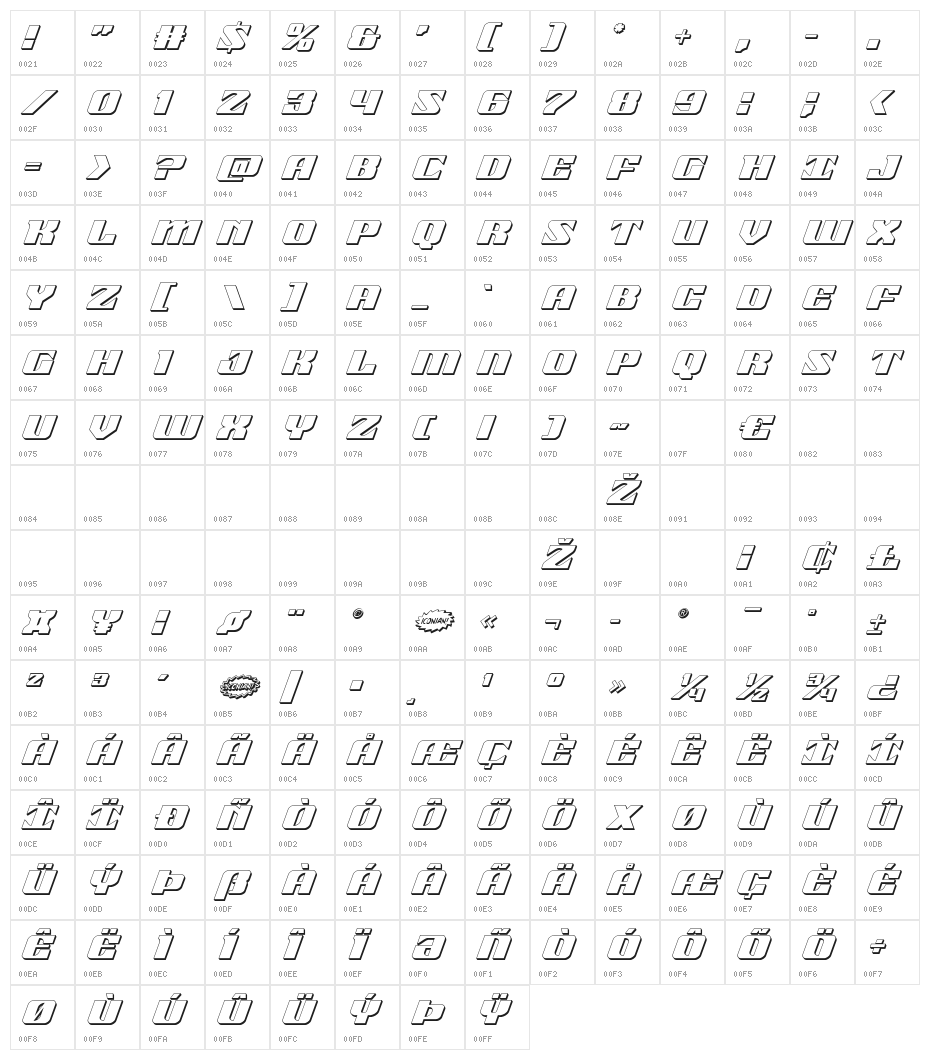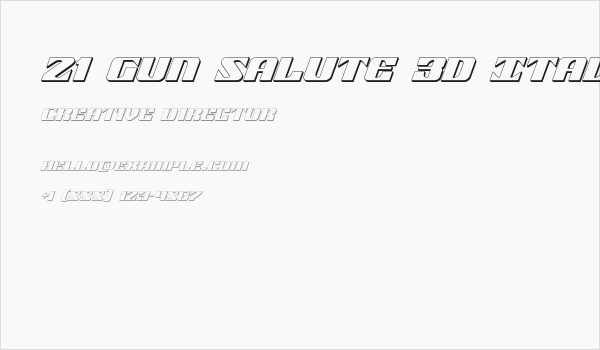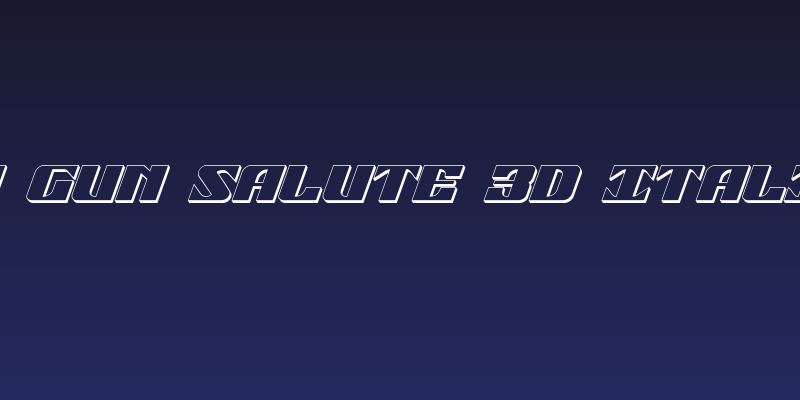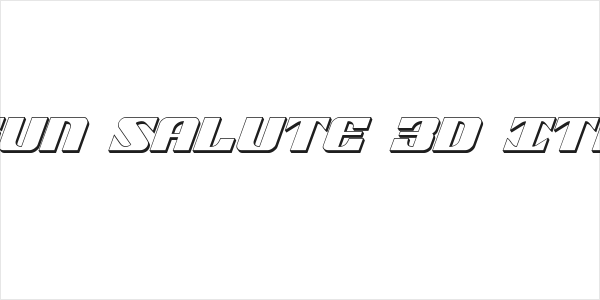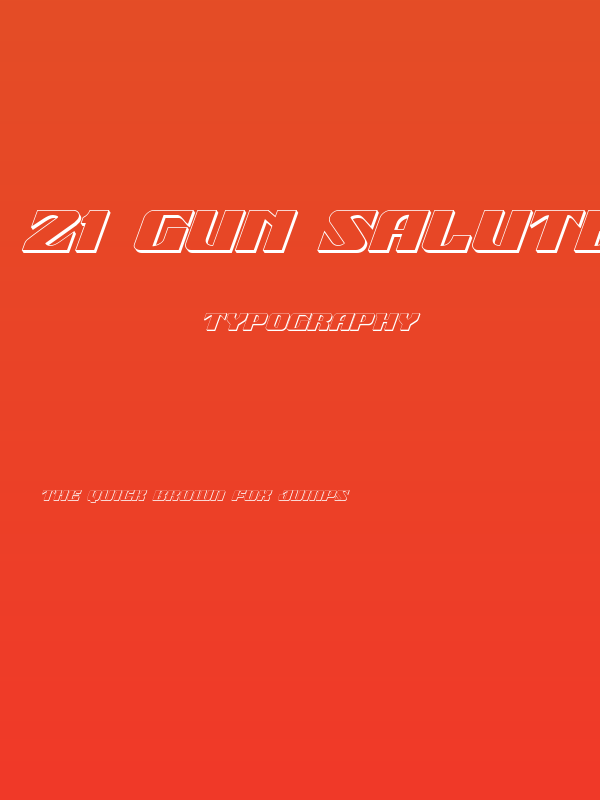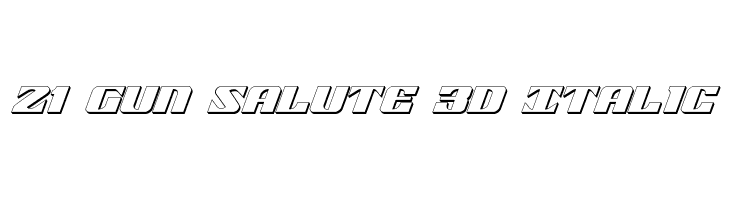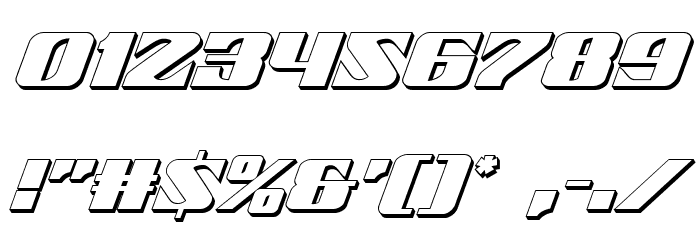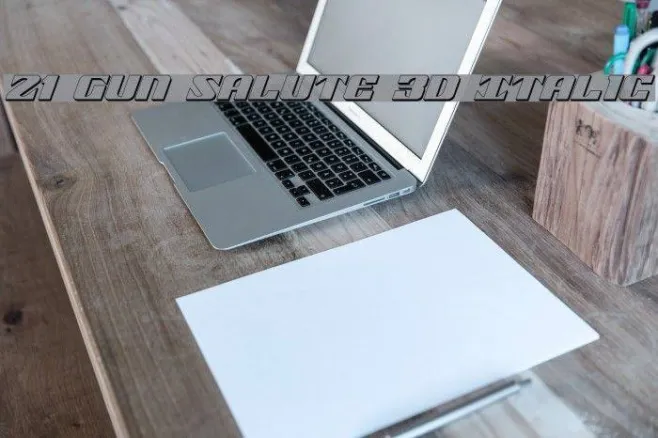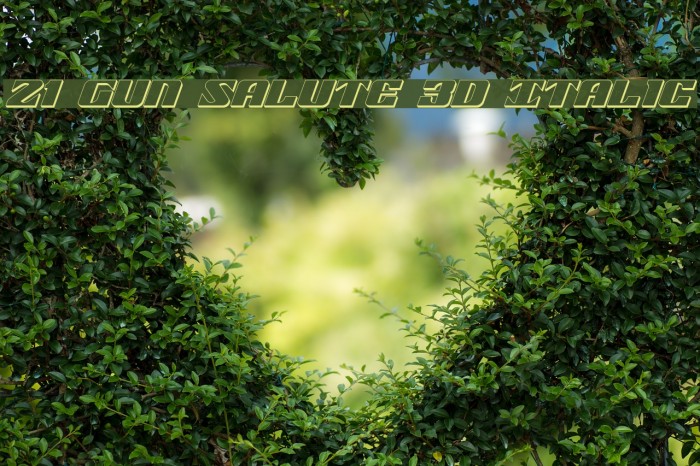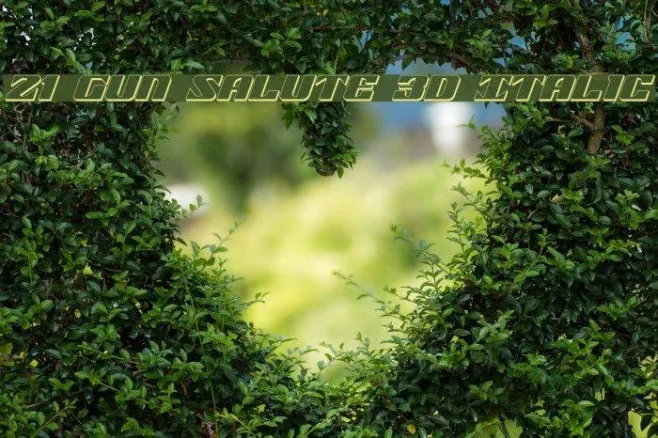
21 Gun Salute 3D Italic Font
| Projets proposés | Ideal for posters, logos, video game titles, and any design needing a modern, impactful look. |
21 Gun Salute 3D Italic